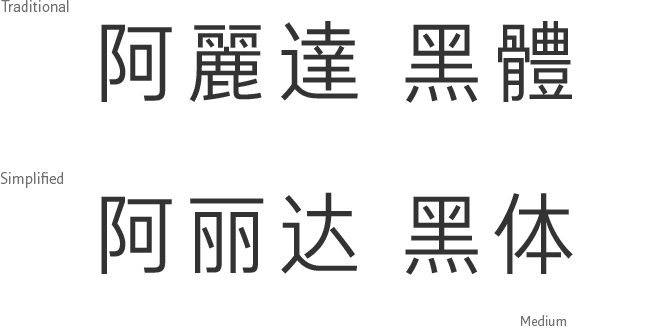
Arita 字体
蕴含着爱茉莉太平洋企业识别,实践分享之价值。
爱茉莉太平洋努力与社会共享美丽的文化,实践分享之价值。Arita字体是爱茉莉太平洋设计并采用的企业字体,无偿提供给大众使用。2016年1月,Arita字体在世界三大顶级设计大奖——德国 iF工业论坛设计奖 (International Forum Design Awards 2016)上获得沟通部门大奖,2015年7月还曾荣获红点设计大奖。
Arita Dotum(韩文)
2005年首次推出的韩文正文用字体,以高品味格调与大众沟通。既有的Dotum体以直线为主,显得有些刻板僵硬。Arita Dotum对Dotum体进行了改进,加入了柔和的曲线创造出了新的字体。